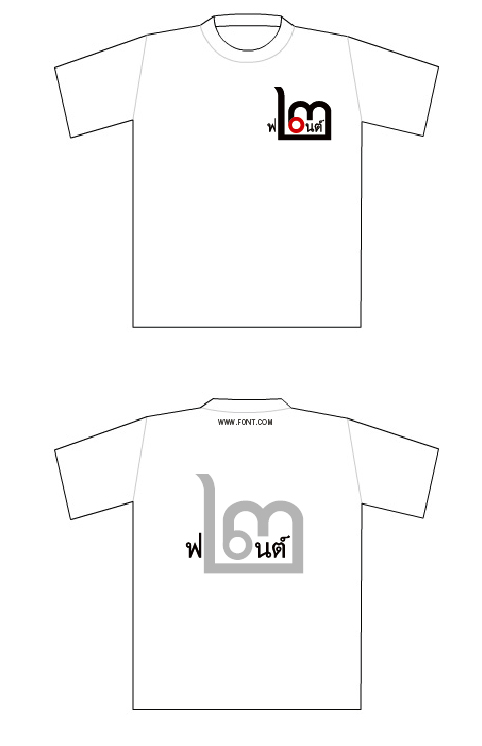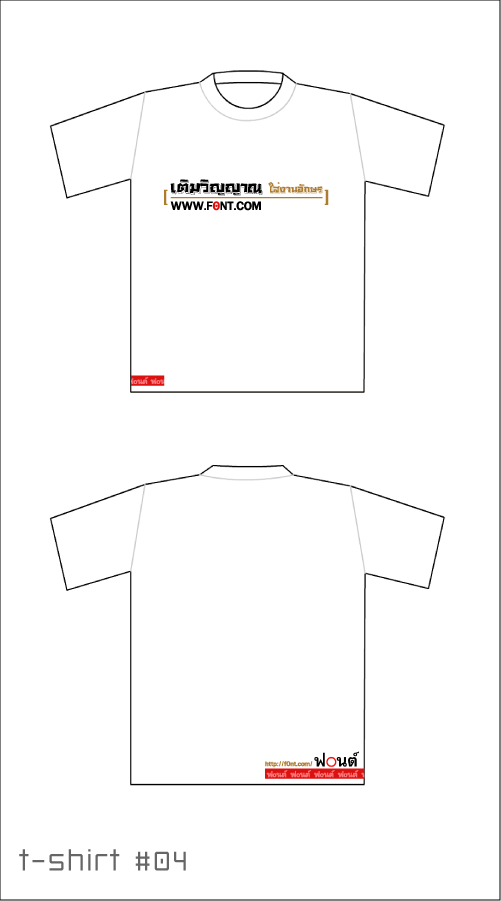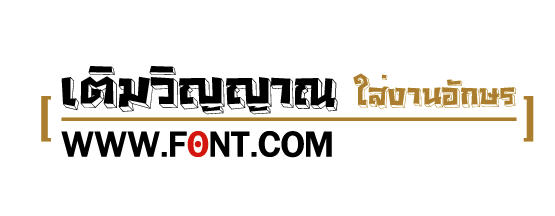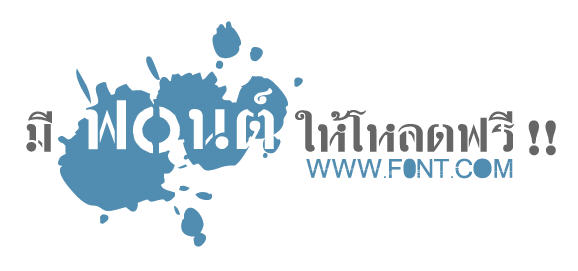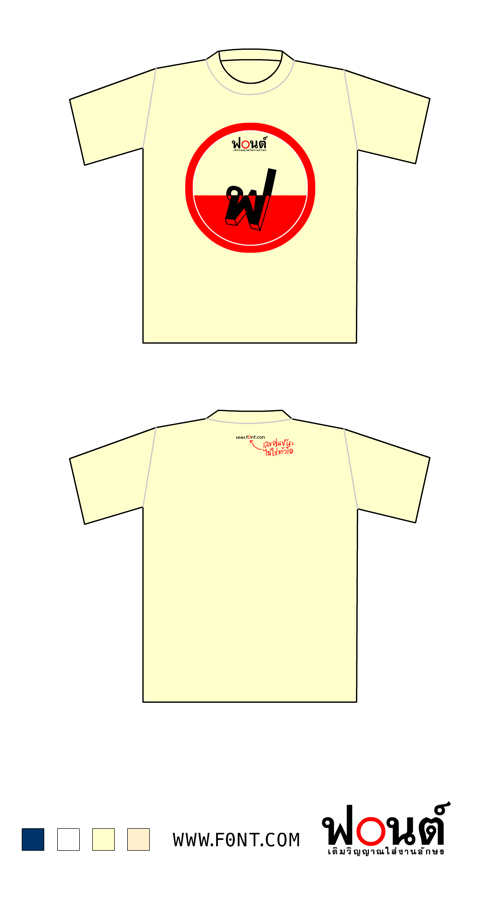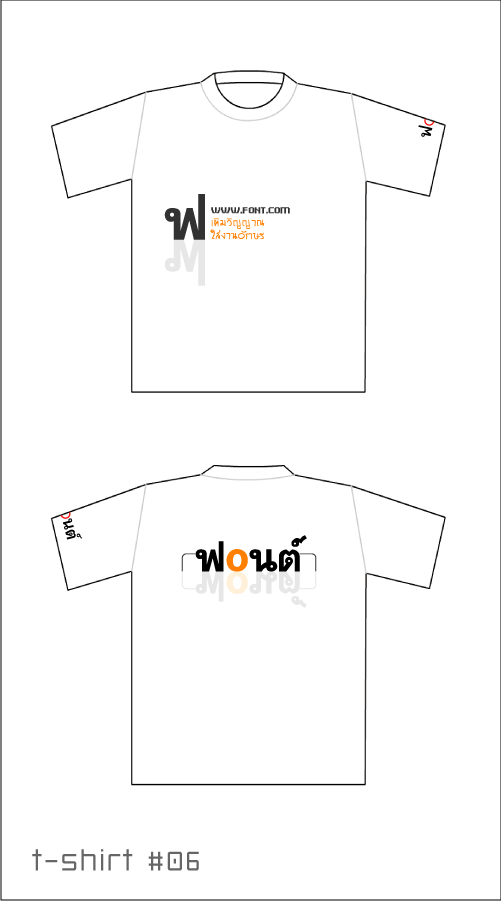
FC7 : เสื้อฟ๐นต์ ภาคสooง
เหมือนเคยเจอเสื้อแนวนี้ที่ไหนด้วยแหละ
//อ๋าห์ เพิ่งเจอ http://www.flickr.com/photos/iannnnn/118175601/in/photostream/
เป็นแบบเสื้อที่ตูส่งประกวดเสื้อ blognone - ผลโหวตได้ที่หนึ่ง แต่หนึ่งในสองเว็บมาสเตอร์บอกไม่กล้าใส่ เลยแป้กไปโดยปริยาย
:07: :07: :07:เคืองๆๆๆ
นั่งคิดเองตั้งนาน ซ้ำซะแล้ว :05: :05: :05:
ไม่เป็นไรหรอก เพราะบล็อกหมีเกินแน่ๆ :21:
เสื้ออรจะไม่ได้ที่1เหรอ แบบว่ามั่นใจมากนะ  :05:
สวัสดีค่ะ เป็นสาวกใหม่ค่ะ ลองมาส่งดูค่ะ :40:
ส่งมั่งๆ  เอาไปอันนึงก่อน
เดี๋ยวคิดออกแล้วค่อยทำอีก
เสื้อหมีสวยมากๆอยากใส่ครับ :25:
ร่วมสนุกด้วยสิ (ยังไงก็จะได้เสื้อฟอนต์ใส่แล้วววว :02:)
แบบ 4
แบบ 5
สุดยอดทั้งนั้น
ชนะ มันทุกแบบเลยไหม
แบบที่ 2 ค่ะ
แบบที่ 3 ค่ะ
อ่อ ลืมขยายข้อความด้านหลังเสื้อค่ะ (ลอกมาจากลายมือแอน)
ชอบของ เคนหมวยก มากๆ!!!!  :30: :30: :30:
ส่งหลังเลิกงาน (ลักลอบทำเสื้อ หัวหน้ามาด้อมๆมองๆทั้งวัน :44:)
ได้แค่นี้แหละ  :42:
แบบ 7